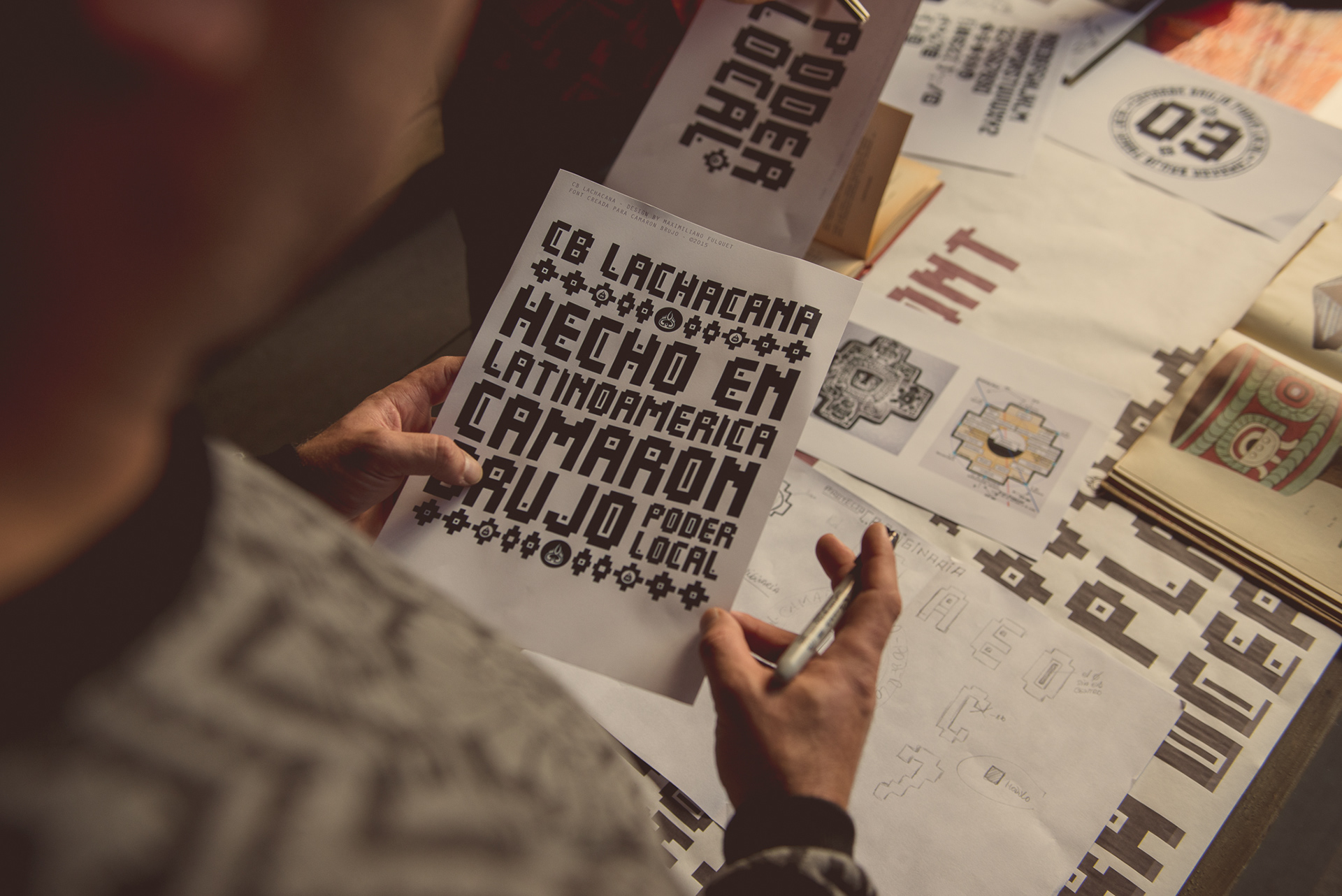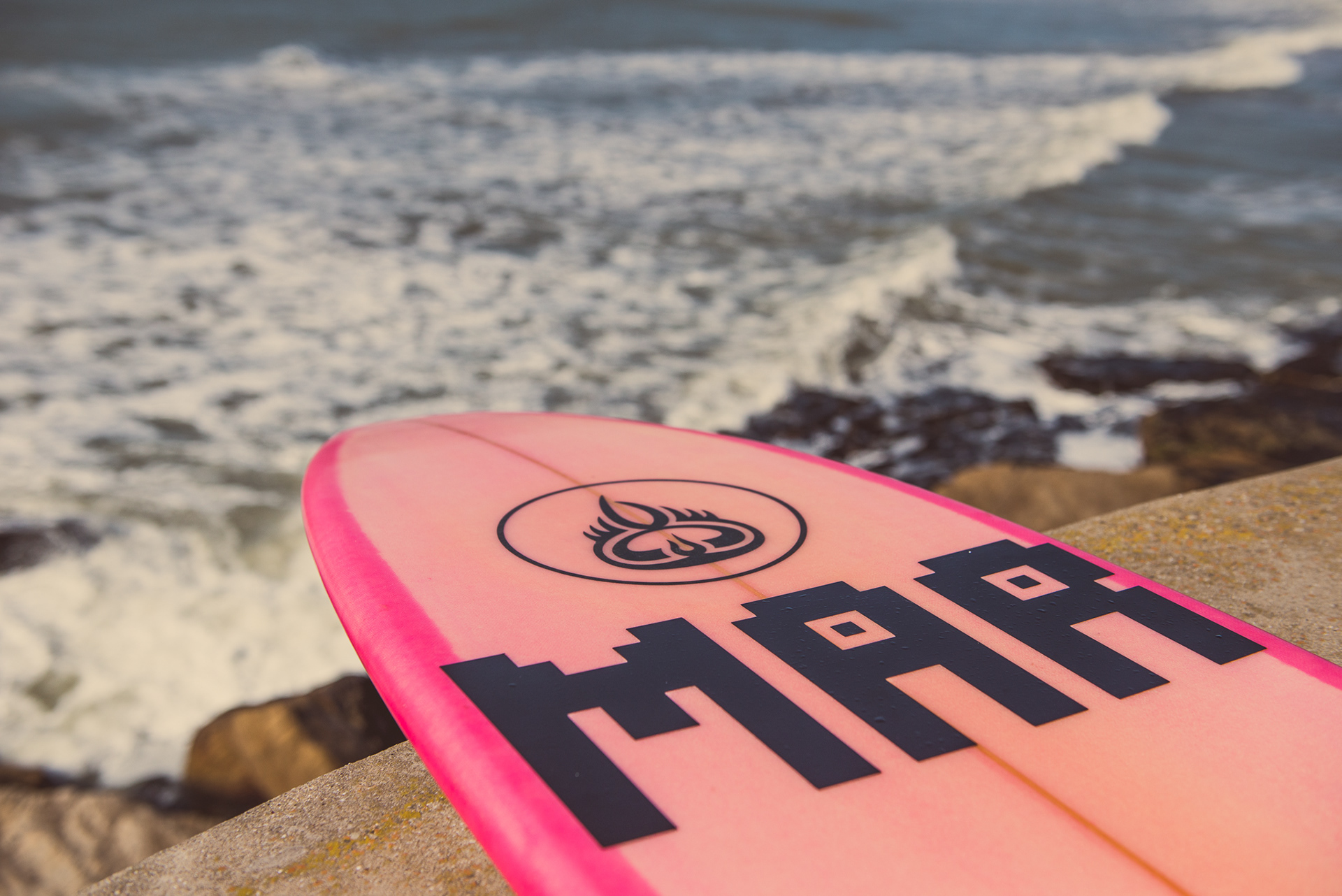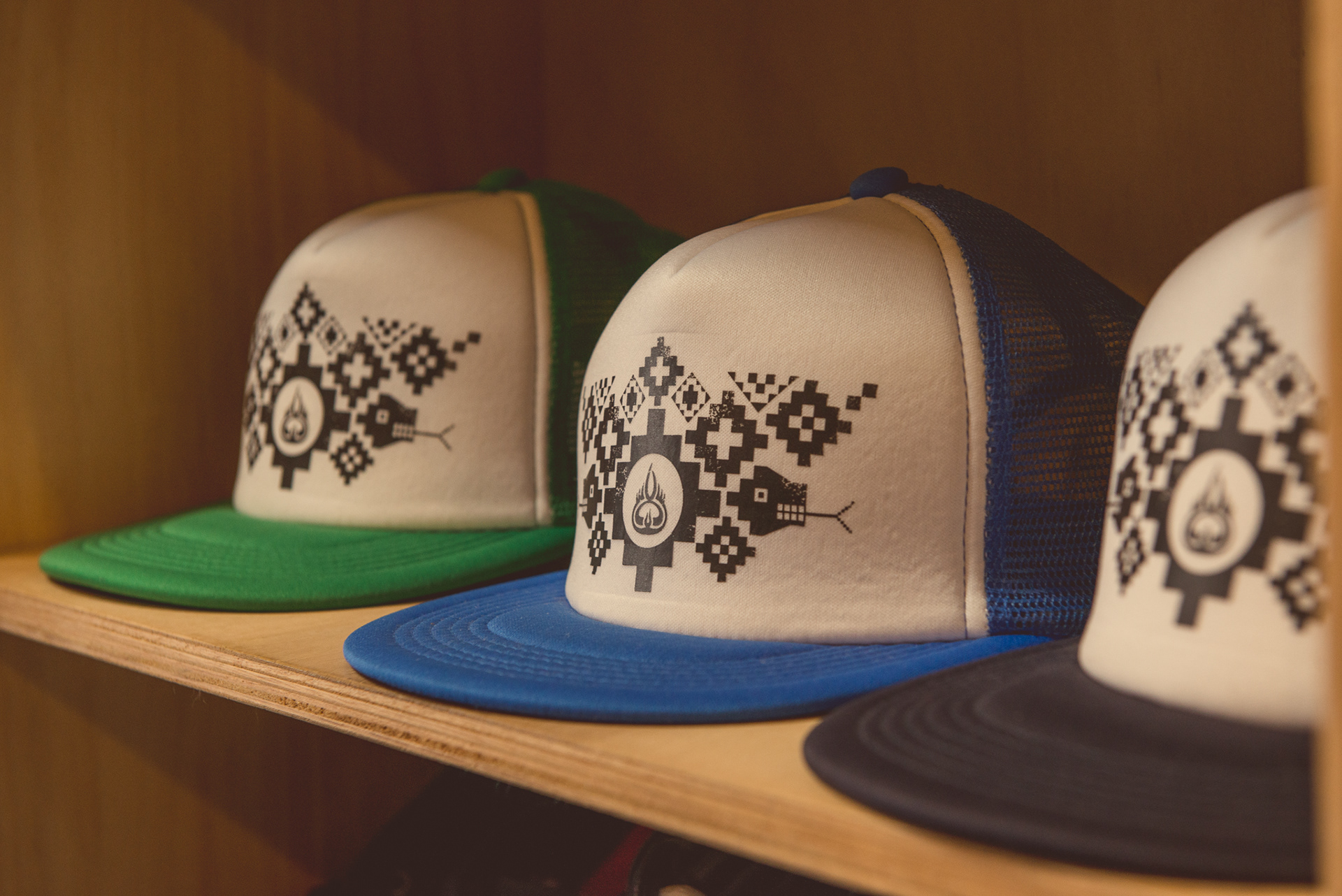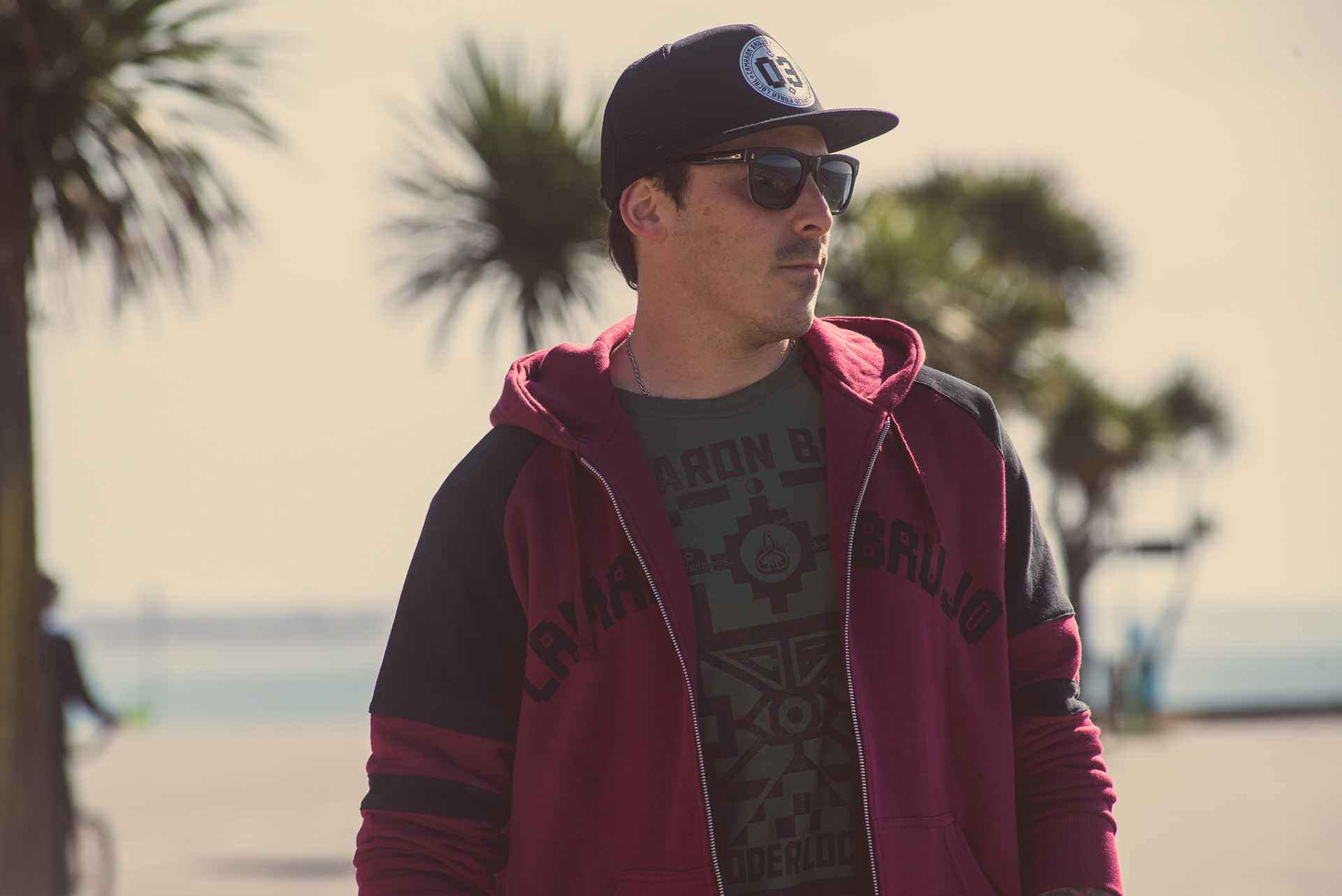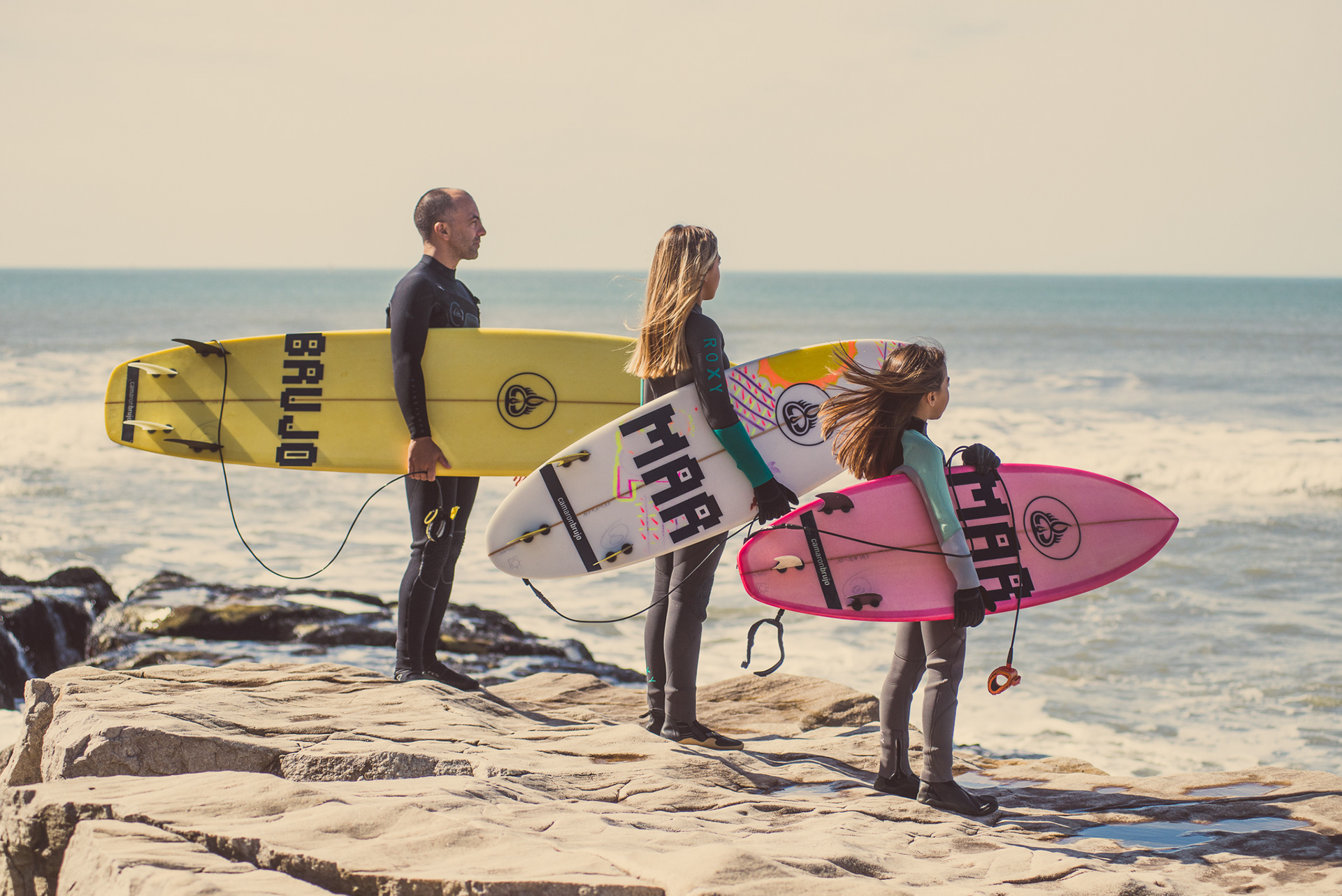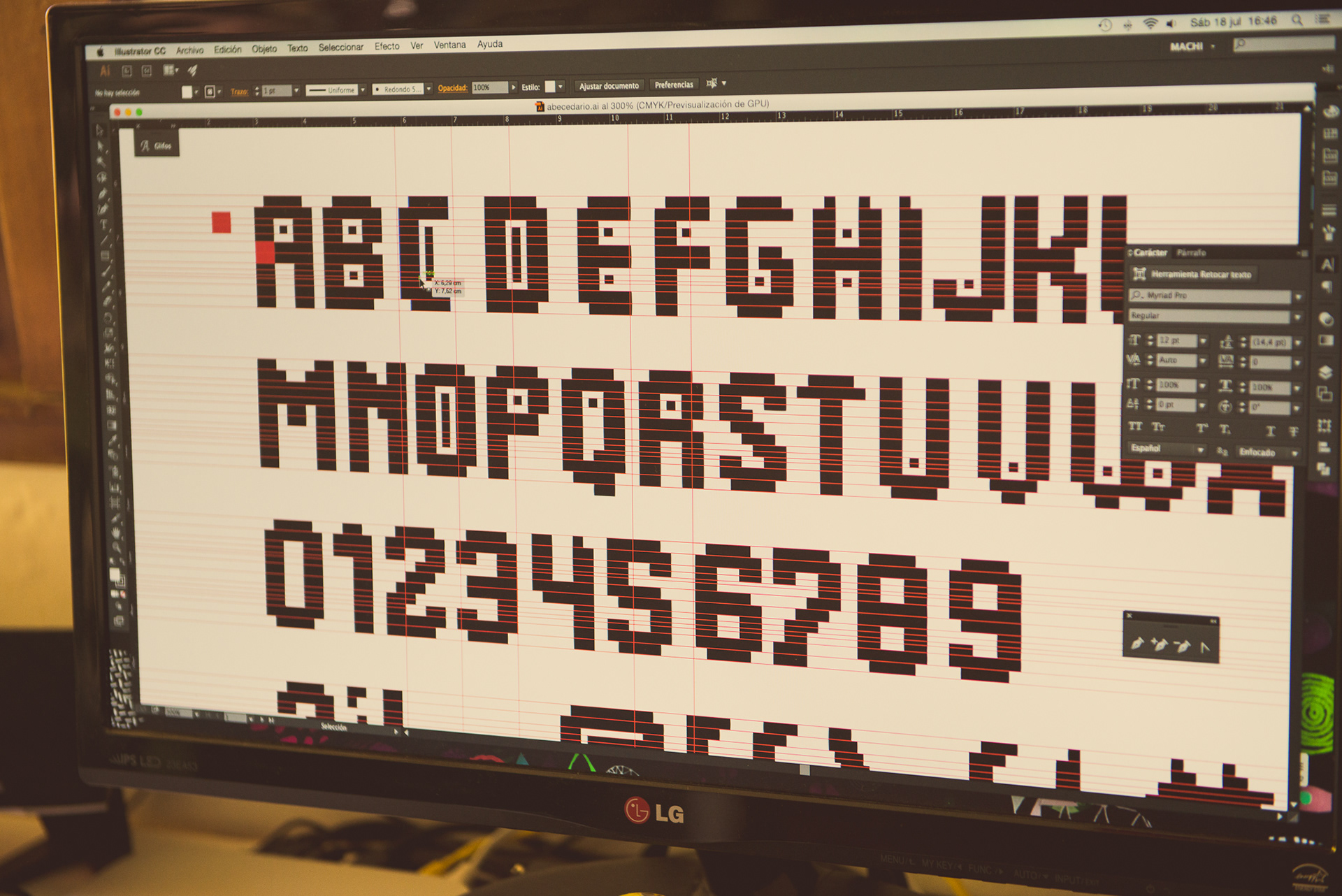
Desarrollo de la tipografía "La Chacana" para Camarón Brujo.
Una fuente construida a partir de la lógica geométrica de la cruz andina, traduciendo su estructura en un sistema tipográfico contemporáneo.